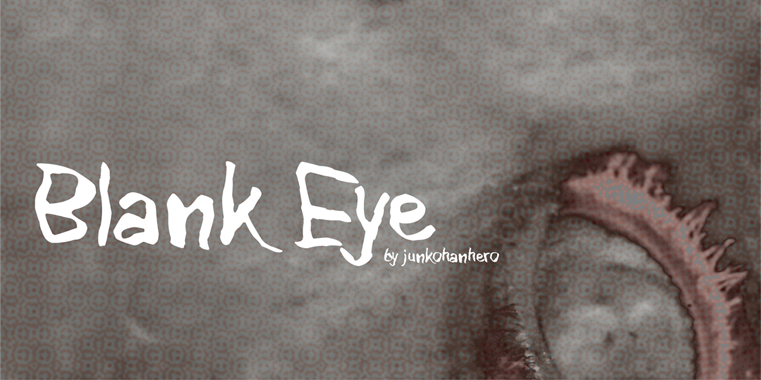
A Blank Eye Font é uma escolha perfeita para projetistas que desejam adicionar um toque inovador à suas criações digitais. Este fonte de exibição, criado pelo designer Hamilton, oferece linhas energizantes e alegres que combinam facilmente com texturas mais sóbrias ou detalhes geométricos modernos. Perfeita para aqueles buscando uma fonte que destaca-se na web ou nos materiais impressos comerciais, esta font é ideal tanto para designers profissionais quanto para criadores de conteúdo. Se você está à procura de uma opção moderna e divertida, a Blank Eye Font será um excelente complemento. Se desejar usar este fonte em projetos comerciais, Hamilton oferece licenças comerciais por meio de um depósito de 15€ ou $20 no PayPal. Após o pagamento, você pode enviar uma mensagem para Hamilton para solicitar a sua chave de licenciamento. Uma opção mais direta é usar o botão doações, que está muito próximo ao botão de download. Não se esqueça, esta fonte não foi criada especificamente para impressões em larga escala ou projetos profissionais que exigem certas regras legais e normas. É perfeitamente adequado para uso pessoal e pequenos projetos comerciais. A Blank Eye Font é um acréscimo encantador à sua coleção de fontes digitais, oferecendo uma pausa divertida em qualquer projeto visual que você estiver criando.